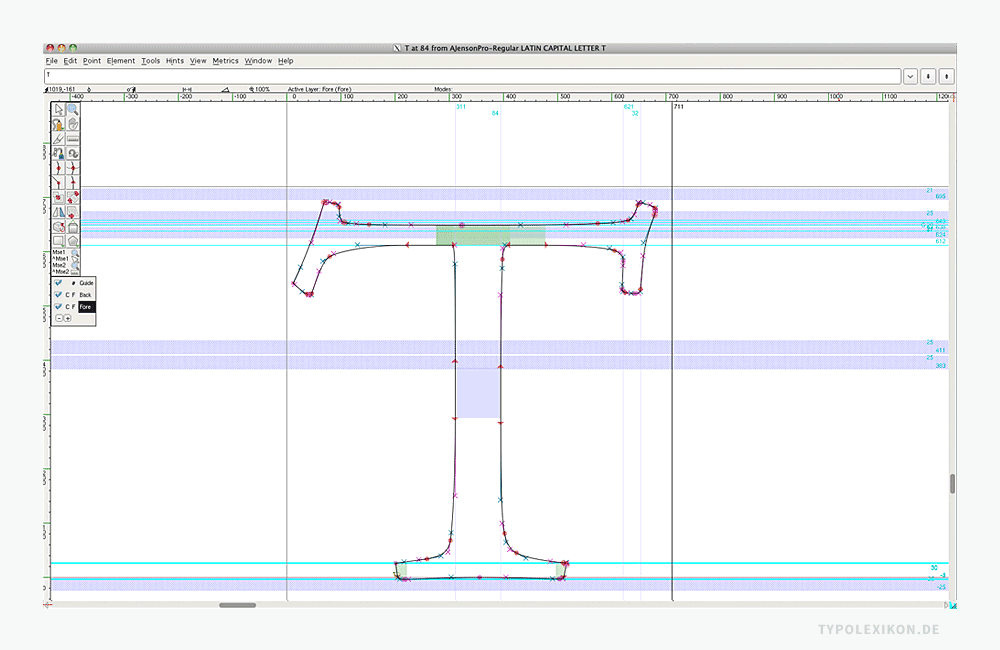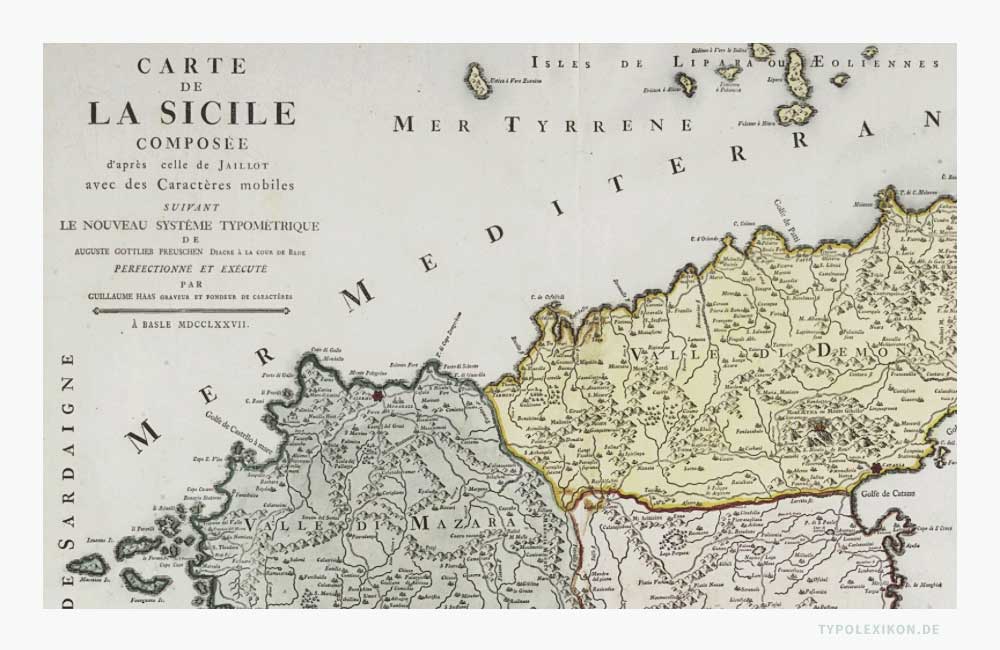
Typometrie
In der Typografie wird der Terminus »Typometrie« je nach Zeitepoche unterschiedlich verwendet. Zum einen bezeichnet Typometrie heute die geometrische Letternarchitektur, zum anderen wurde damit im 18. Jahrhundert ein Buchdruckverfahren von Landkarten beschrieben.
1. Geometrische Konstruktion von Schriftzeichen
Unter Typometrie versteht man heute die euklidisch-geometrische Konstruktion von Schriftzeichen: Letternvermessung, Zeichen(geo)metrie, Letternarchitektur. Es handelt sich um ein Segment der Schriftgestaltung (Schriftentwurf, Type Design), das die gestaltlichen Gesetzmäßigkeiten und Größenbeziehungen (Proportionen) zwischen Linien, Schriftlinien und Flächen behandelt, die zur Konstruktion von Buchstaben, Ziffern und Sonderzeichen – unabhängig von den Spezifika der Schriftklassifikation – notwendig sind.
Der Terminus »Typometrie« ist als neu interpretiertes Determinativ-Kompositum eine Zusammensetzung aus den altgriechischen Wurzelnomen »typos« (ursprünglich Schlag, Stoß, Eindruck, später auch Type im Sinne von Druckbuchstabe) und »metrie« als Suffix zur Bildung von Substantiven zur Bezeichnung von Wissenschaften mit der Bedeutung »Messung, Vermessung« bzw. »metron« für »Maß«.
Diese im Jahre 2003 neu interpretierte Wortschöpfung des Typografen Wolfgang Beinert (*1960) bezeichnet in ihrer konkreten Bedeutung von »Letternvermessung« die elementare, jahrhundertelang von Schriftentwerfern praktizierte Technik der exakten geometrischen Konstruktion von Buchstaben, die, obwohl unabdingbare »conditio sine qua non«, in der offiziellen Terminologie bislang fehlte und nunmehr definiert sowie historisch-bibliographisch dokumentiert in den typografischen Diskurs eingebracht wird.
Modellalphabete der Renaissance
Die Wiederentdeckung der antiken Kultur durch die italienischen Humanisten der Renaissance belebte auch das Interesse an den griechischen und römischen Schriftstilen. Inspiriert von der Epigraphik der Römer und ihrer archetypischen Capitalis monumentalis auf der Trajans-Säule (Trajanisches Alphabet) entstanden in der zweiten Hälfte des 15. Jahrhunderts erste systematische Anleitungen zur geometrisch exakten Konstruktion von Buchstaben.
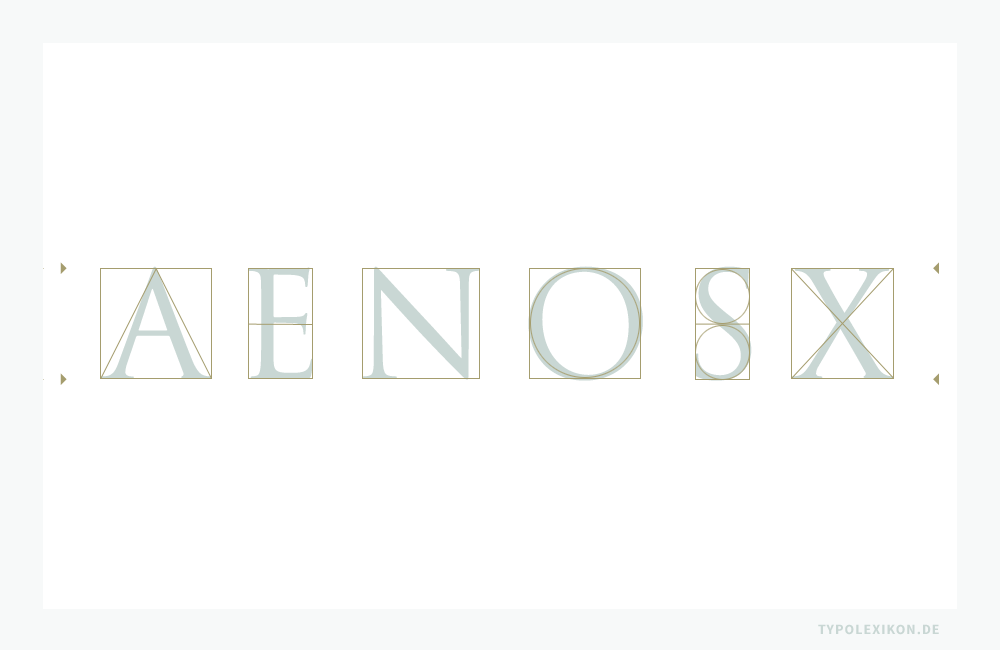
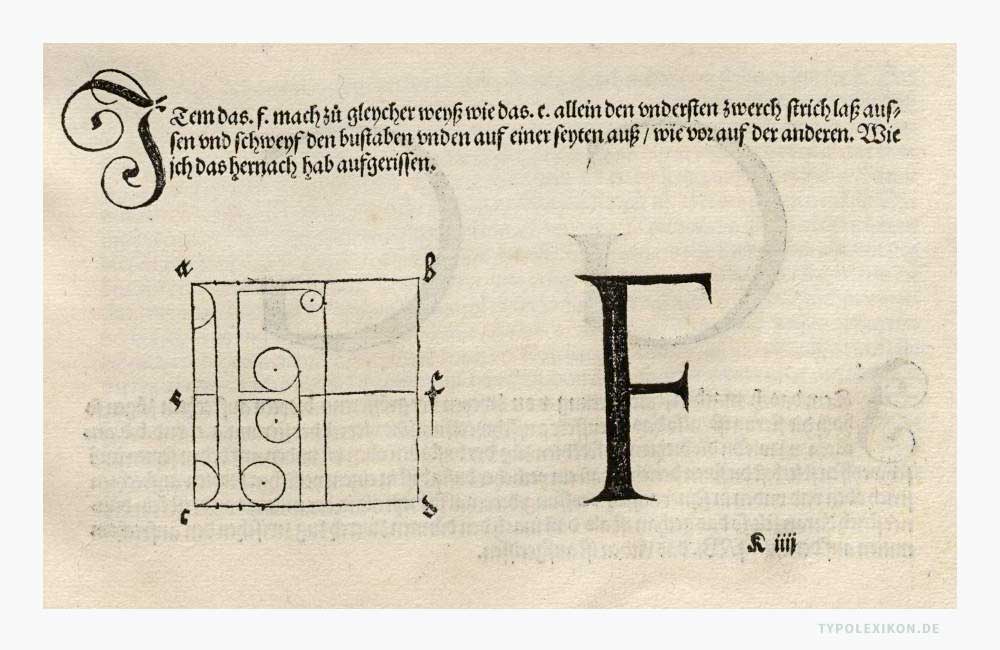
Vor allem die neuen »Künstler-Ingenieure« der Renaissance – beispielsweise Ferdinando Ruano (o.A.–1560, Kalligraf an der Vatikanischen Bibliothek), Vespasiano Amphiareo (um 1490–1563, Kalligraf in Florenz und Venedig), Wolfgang Fugger (um 1515–1568, Kalligraf in Nürnberg), Geoffroy Tory (um 1480–1533, Kalligraf und Typograf in Paris), Albrecht Dürer (1471–1528, Maler, Grafiker, Mathematiker und Kunsttheoretiker in Nürnberg), Francesco Torniello da Novara (um 1490–1589, Typograf und Schriftschneider in Mailand), Luca Pacioli (um 1445–1514 oder 1517, Kalligraf, Mathematiker und Franziskanerpater in Italien), Damiano da Moile (um 1450–1500/1510, Buchbinder, Kalligraf und Typograf in Parma und Venedig), Leonardo da Vinci (1452–1519, Künstler und Universalgelehrter in Italien und Frankreich) und Felice Feliciano (1433–1479, Kalligraf in Rom) – orientierten sich am Vorbild dieser mit Zirkel und Lineal, die in der Metrologie zu den ersten analogen Messinstrumente zählen, skizzierten Modellalphabete, die sich mathematisch oft auch an der »proportio divina«, der göttliche Proportion (siehe Goldener Schnitt), orientierten.
Die erste überlieferte, noch handschriftliche Abhandlung zur typometrischen Rekonstruktion der römischen Kapitale ist das heute im Vatikan aufbewahrte »Alphabetum Romanum« aus dem Jahr 1463, ein in Verona verfaßtes Manuskript des italienischen Kalligrafen und Inkunabeldruckers Felice Feliciano.
1466 druckte die universitätseigene Offizin der Pariser Sorbonne »De caracteribus institutio« von Guillaume Fichet und 1470 erschien das »Alphabetum« des Damiano da Moile in Parma. 1509 folgte dann die berühmte »Divina Proportione« von Luca Pacioli (siehe Goldener Schnitt), der Leonardo Fibonaccis (um 1170–1240, Mathematiker in Pisa) geniale, aus dem 12. Jahrhundert stammende Studien zu den rekursiven Bildungsgesetzen (Fibonacci-Folge) auf die Letternkonstruktion anwandte.
Ein Traktat von Francesco Torniello da Novara, »Opera del modo de fara le littere maiuscole antique, con mesura de circino & resone de penna«, wurde 1517 gedruckt. Das Werk »La operina de Ludouico Vicentino, da imparare ‚di scrivere‘ littera Cancellarescha« des Ludovico degli Arrighi (1475 –1527, Kalligraf und Typograf in Rom) das speziell den Guß und Druck der sogenannten »Kanzleischrift« behandelte, datiert von 1522.
1525 erschien dann Albrecht Dürers epochale »Underweysung der messung mit dem zirckel un richtscheyt in Linien, ebenen und gantzen corporen, durch Albrecht Dürer zusammen getzogen und zu nutz allen kunstliebhabenden mit zugehörigen figuren in truck gebracht im jar MDXXV«. Den dritten Teil seiner geometrischen Summa widmete er der Konstruktion von typografierten Initialen und erstmals auch den Minuskeln der gotischen Textura (explizit den Kleinbuchstaben der 1517 entwickelten Fraktur). Als Referenzsysteme verwendete Dürer Quadrate und kleine Kreise, nicht jedoch den bei seinen Vorgängern üblichen eingeschriebenen Kreis; auch das unseren modernen computergenerierten Schriftzeichen unterlegte Raster geht auf Dürer zurück.
Von großer Bedeutung für die Entwicklung der Typografie war das 1529 in Paris durch Gilles de Gourmont (1499–1533, Typograf in Paris) gedruckte Hauptwerk von Geofroy Tory (des Mentors von Claude Garamond) mit dem poetischen Titel:« Champfleury. Auquel est contenu Lart & Science de la deue & vraye Proportion des Lettres Attiques, qu’on dit autrement Lettres Antiques, & vulgairement Lettres Romaines proportionnées selon le Corps & Visage humain ». Tory kritisierte darin die starren Proportionsregeln von Luca Pacioli, die der schöpferischen Individualität zu wenig Spielraum ließen, und stellte ihnen den menschlichen Körper und das Antlitz als Bezugssysteme seiner sogenannten« construction anthropomorphique »gegenüber.
1531 erschien Giovanni Antonio Taglientes (um 1460–1528, Kalligraf und Verleger in Venedig) »Lo presente libro insegna La vera arte de lo excellente scrivere de diverse varie sorti de littere«, 1535 der »Thesauro de scrittori: opera artifisiosa laquale con grandissima arte si per pratica come per geometria insegna a scrivere diversa sorte littere…« von Sigismondo Fanti (um 1492–1527, italienischer Sprachgelehrter und Typograf) und 1540 schließlich das berühmte »Libro Nuovo« von Giambattista Palatino (1515–1575, Kalligraf und Schriftsteller in Rom). Im selben Jahr 1540 wurde bei Venturino Roffinello (Schaffensperiode um 1530-1559, Kalligraf Venedig und Mantua) in Venedig das Werk »Li diece libri della Pirotechnica« gedruckt, das erstmals die Drucktechniken, das Gießen der Buchstaben und deren Metallzusammensetzung behandelte; verfaßt wurde es von Vannoccio Biringuccio (1480–1537, Ingenieur, Architekt, Büchsenmacher und Chemiker in Rom), der gemeinsam mit Georgius Agricola (1494–1555, Gelehrter in Italien und Deutschland) als Vater der Metallurgie gilt.
| ↑4 | Anmerkung: Als Chemitypie wird ein Verfahren bezeichnet, dass eine – auf einer Metallplatte ausgeführten – Radierung oder Gravierung in einen erhabenen Stempel verwandelt, der sich dann auf der Buchdruckerpresse abdrucken lässt. Quelle: F. A. Brockhaus, 1846. |